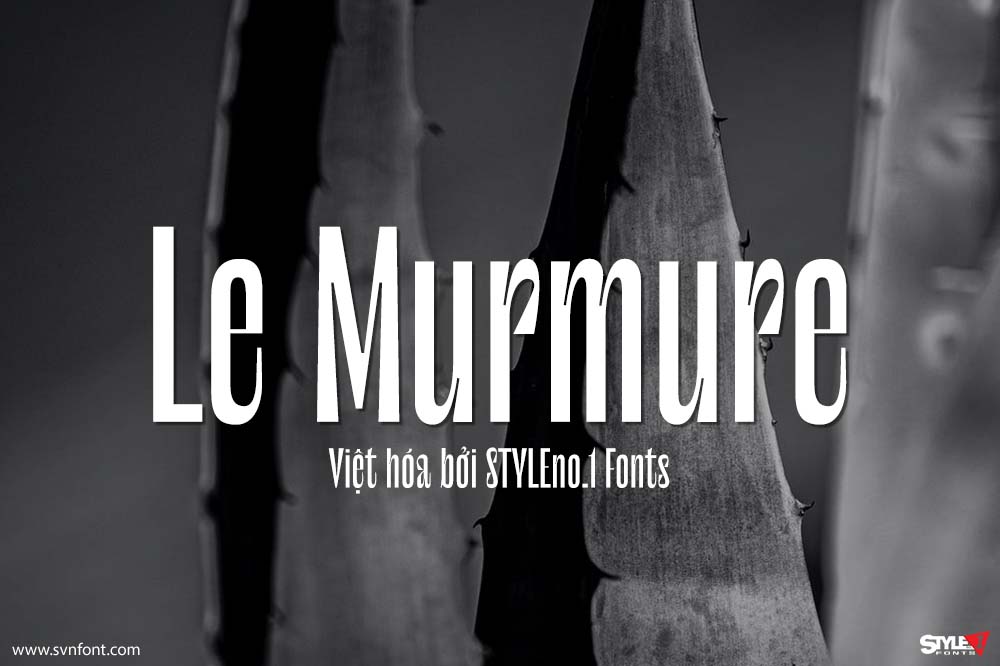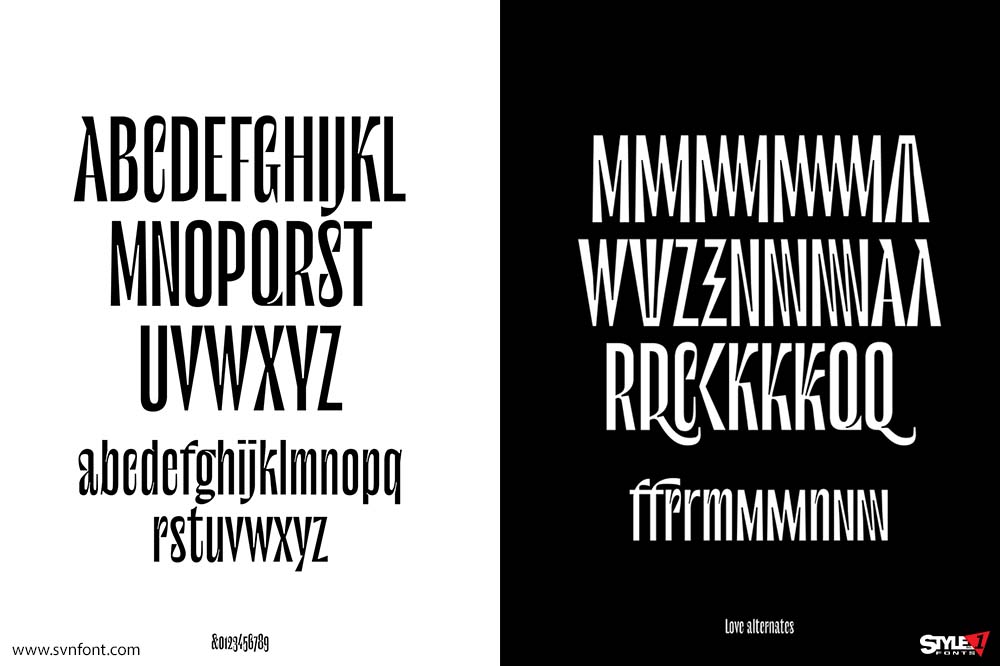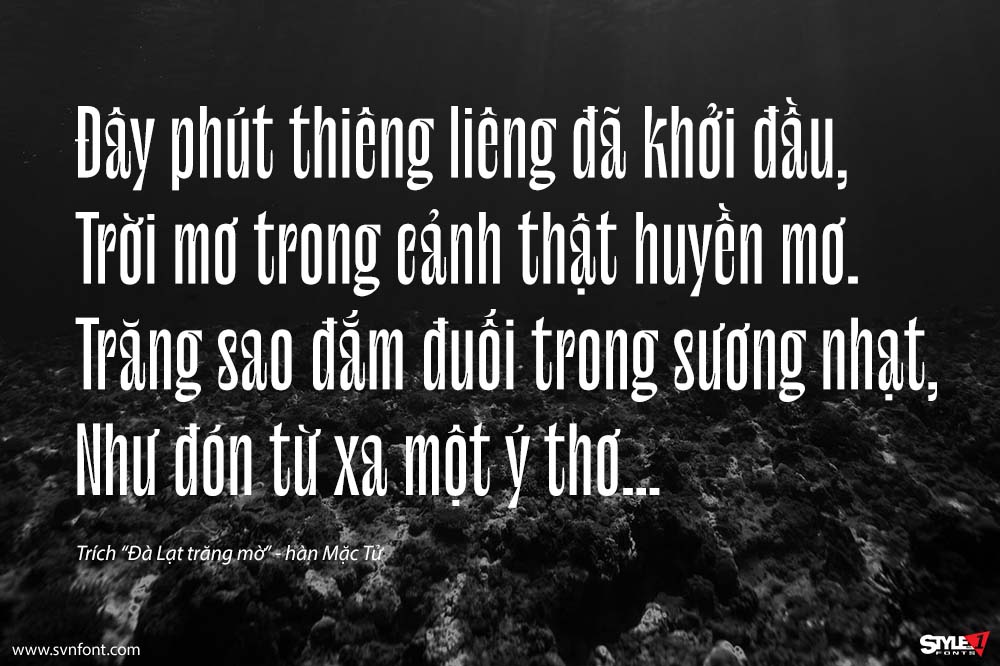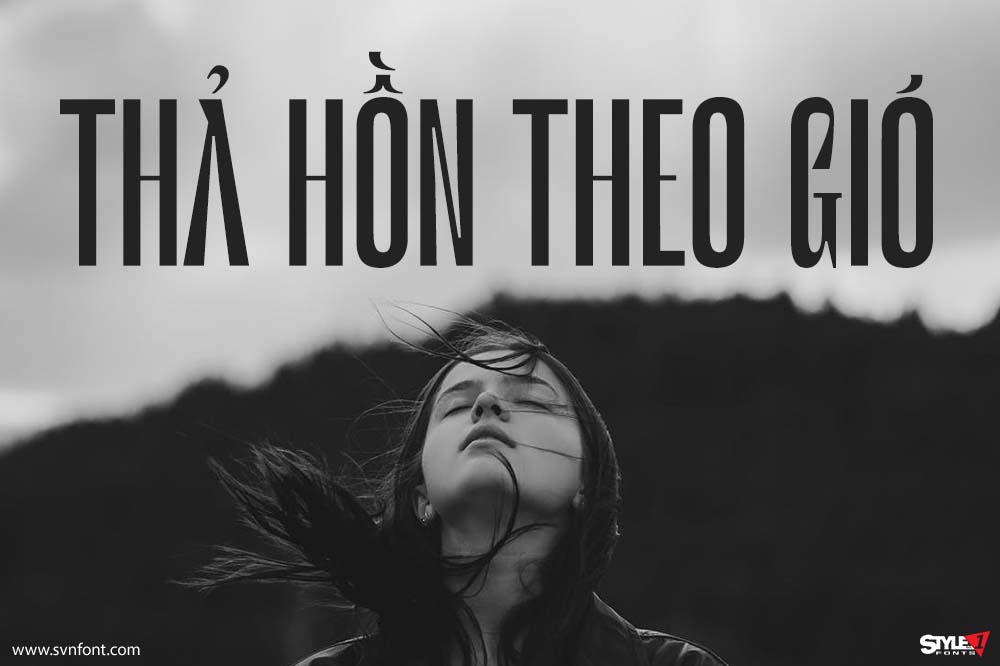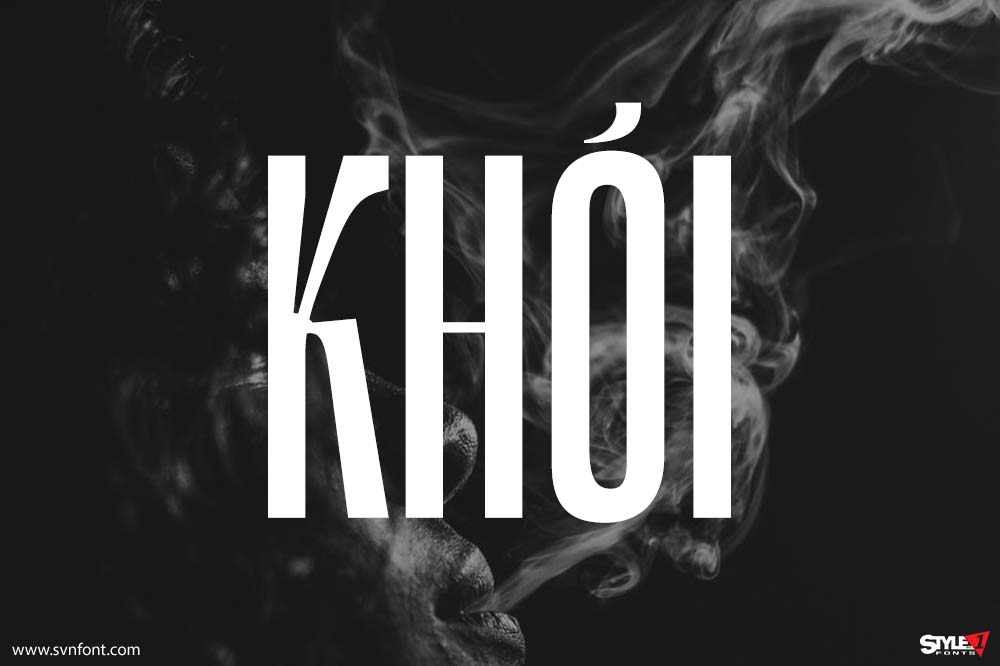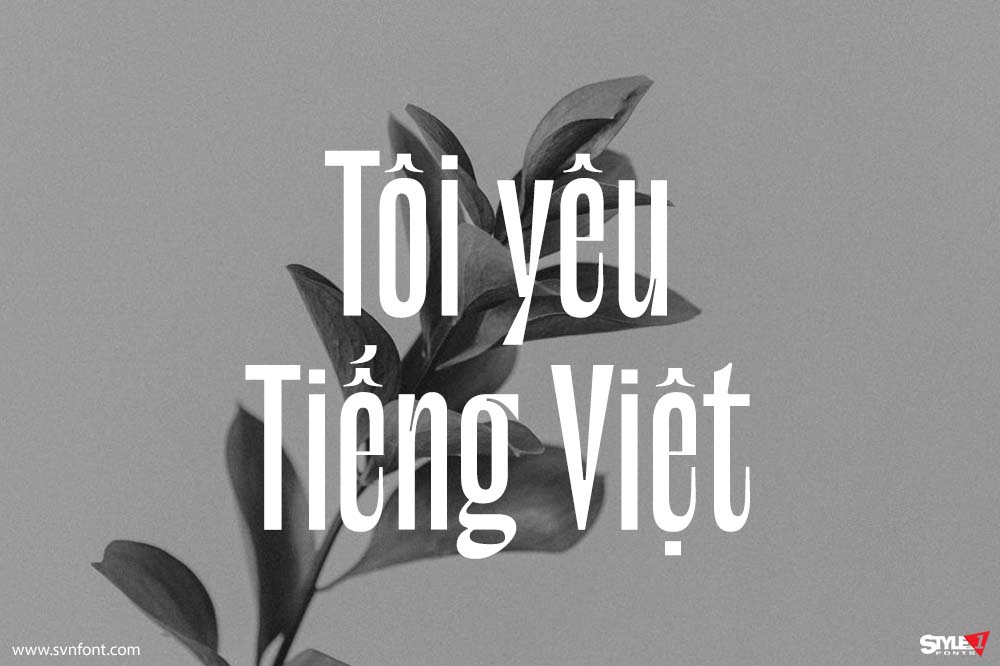
Font Việt Hóa SVN - Le Murmure Mang Phong Cách Sang Trọng, Thanh Lịch
Le Murmure là một sans serif typeface kiểu hẹp, tương phản cao, thanh lịch, cô đọng và cực kỳ ấn tượng. Font thích hợp cho branding, logo, tiêu đề,...
Nhà thiết kế: Jeremy Landes, Alexander Slobzheninov (Cyrillic), George Triantafyllakos (Greek)
Nhà phát hành: Velvetyne Type Foundry
Việt hóa: STYLEno.1 Fonts